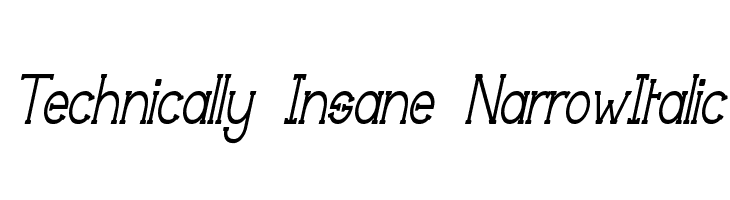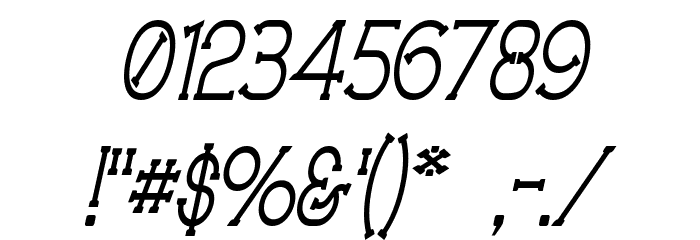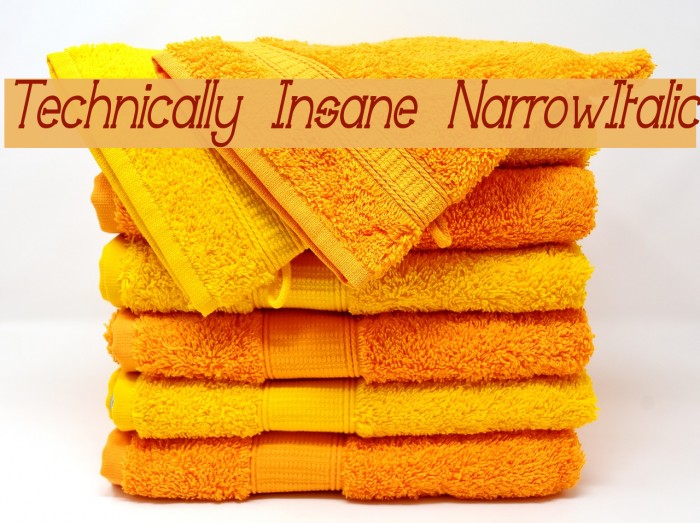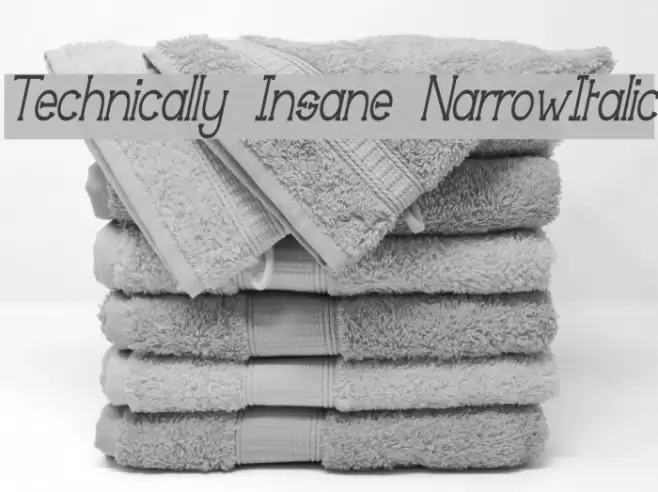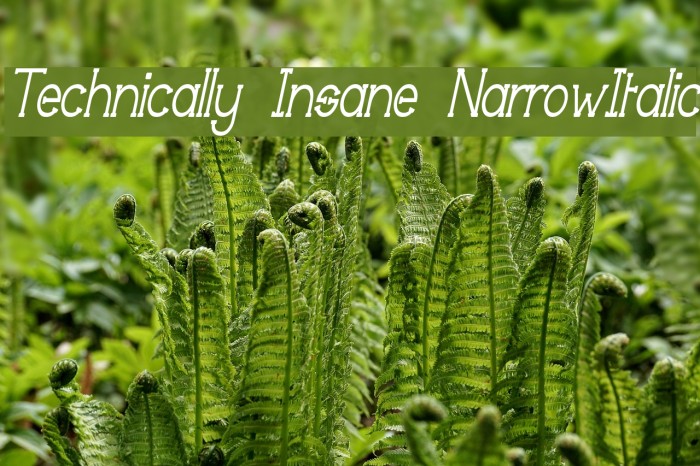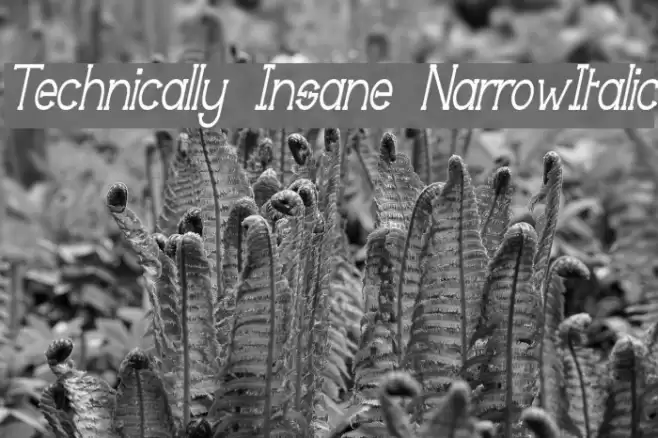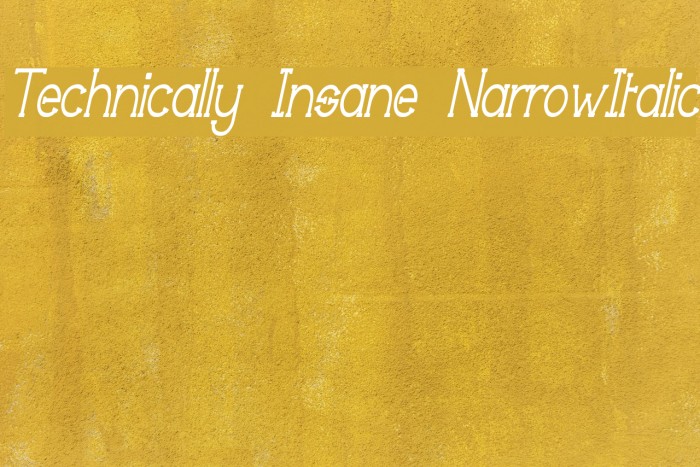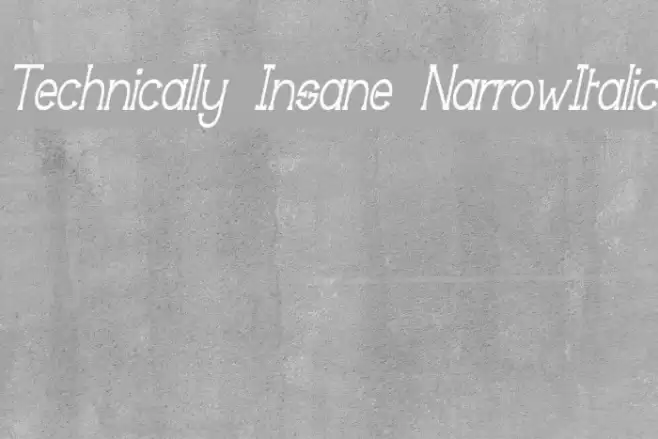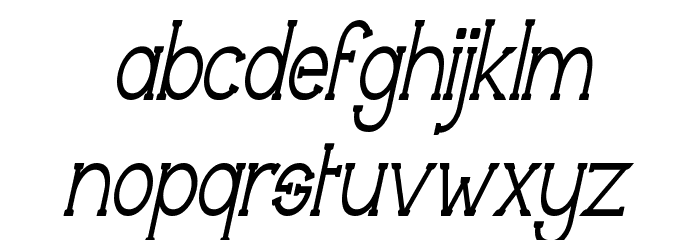
Technically Insane NarrowItalic Font
Fonts by Graham Meade - GemFonts
| Caso de uso | Headlines, Logos, Advertising |
| Projetos propostos | Ideal for branding, advertising, and editorial design where a modern and energetic feel is desired. |